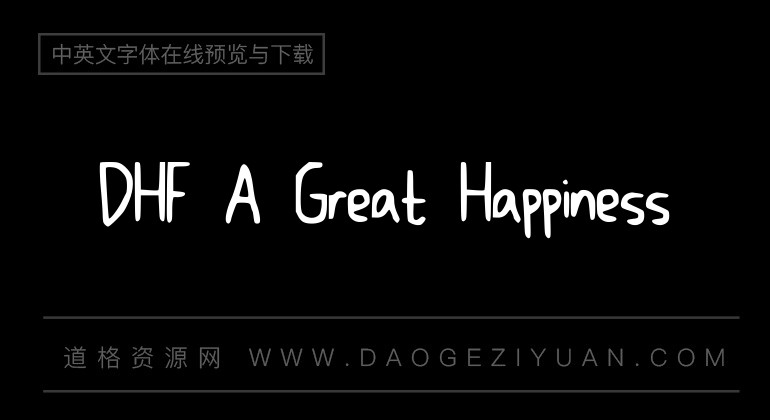
DHF A Great Happiness
DHF A Great Happiness字体是一款由DHF设计的英文字体,它具有简洁、清新、活泼的特点,让文字充满活力,更加有趣。它具有良好的可读性,可以用于广告、标语、标题等场景,可以让文字更加醒目,吸引眼球。此外,它还具有良好的空间感,可以让文字更加精致,更具有层次感。
DHF A Great Happiness是一款非常不错的手写艺术字体,具有很好的视觉感,适合于文化类的宣传设计、商业类品牌的广告和产品包装设计以及个性化文字排版等较多场景。